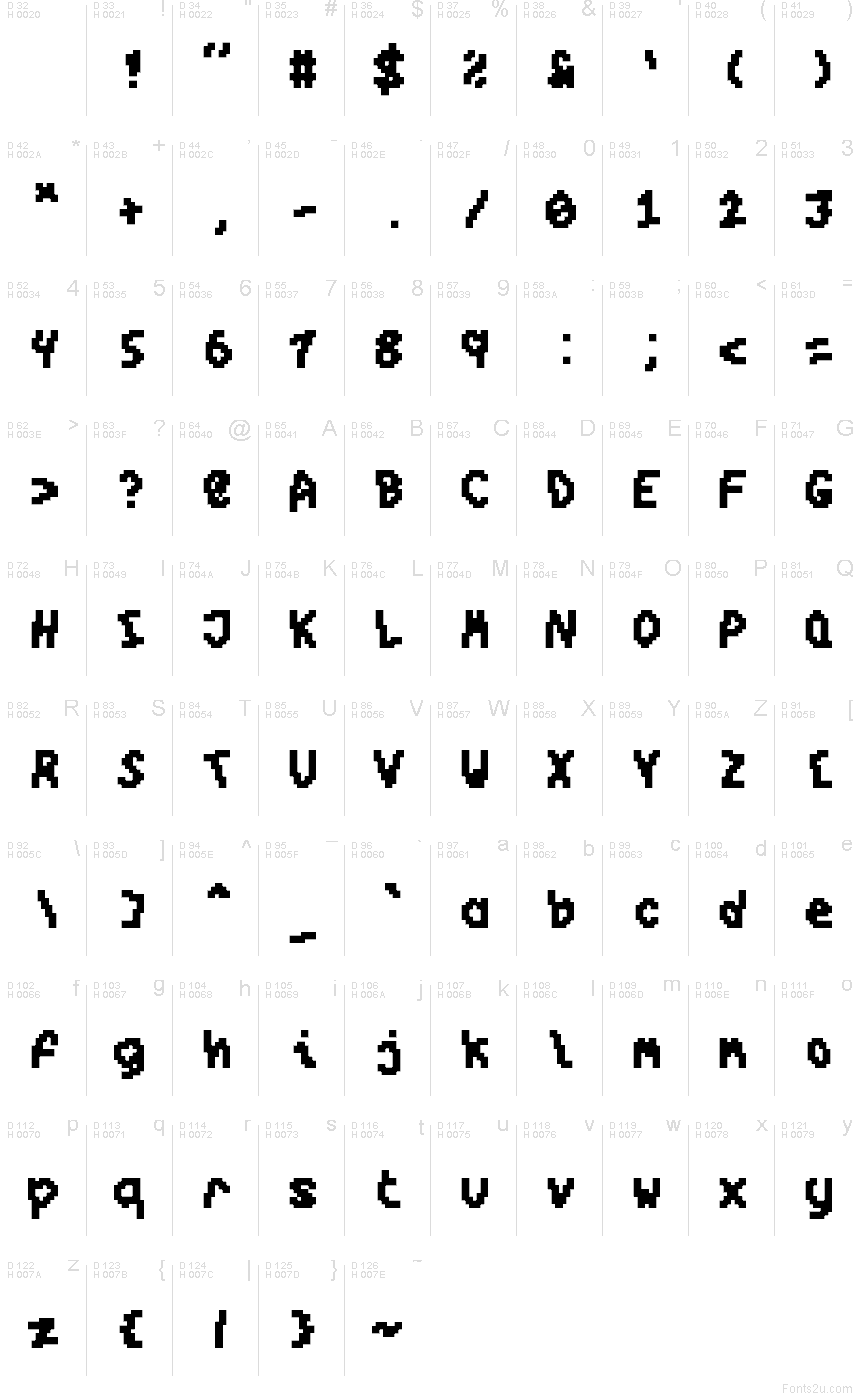
Boiled Pasta es una tipografía bitmap de píxeles gratuita con un ritmo tambaleante y desenfadado, que se siente más hecha a mano que rígidamente cuadriculada. Sus letras son gruesas y escalonadas, pero las formas se hinchan e inclinan de una manera relajada que le da a la fuente un aire juguetón de pantalla antigua, en lugar de la dureza de los juegos arcade.
Esto la convierte en una opción natural para game jams, portadas de fanzines, titulares de pósteres, gráficos para merchandising y superposiciones de streams, donde un poco de imperfección ayuda a que las letras se sientan humanas. Como fuente gratuita, también funciona muy bien para tarjetas de título y palabras cortas estilo logotipo, especialmente cuando buscas una textura de píxel con una energía más suave y divertida que la de un bitmap retro de bordes duros.
La fuente es 1:1 a 16px.
Boiled Pasta
Simple pixel font based on the UI font of Baba Is You.